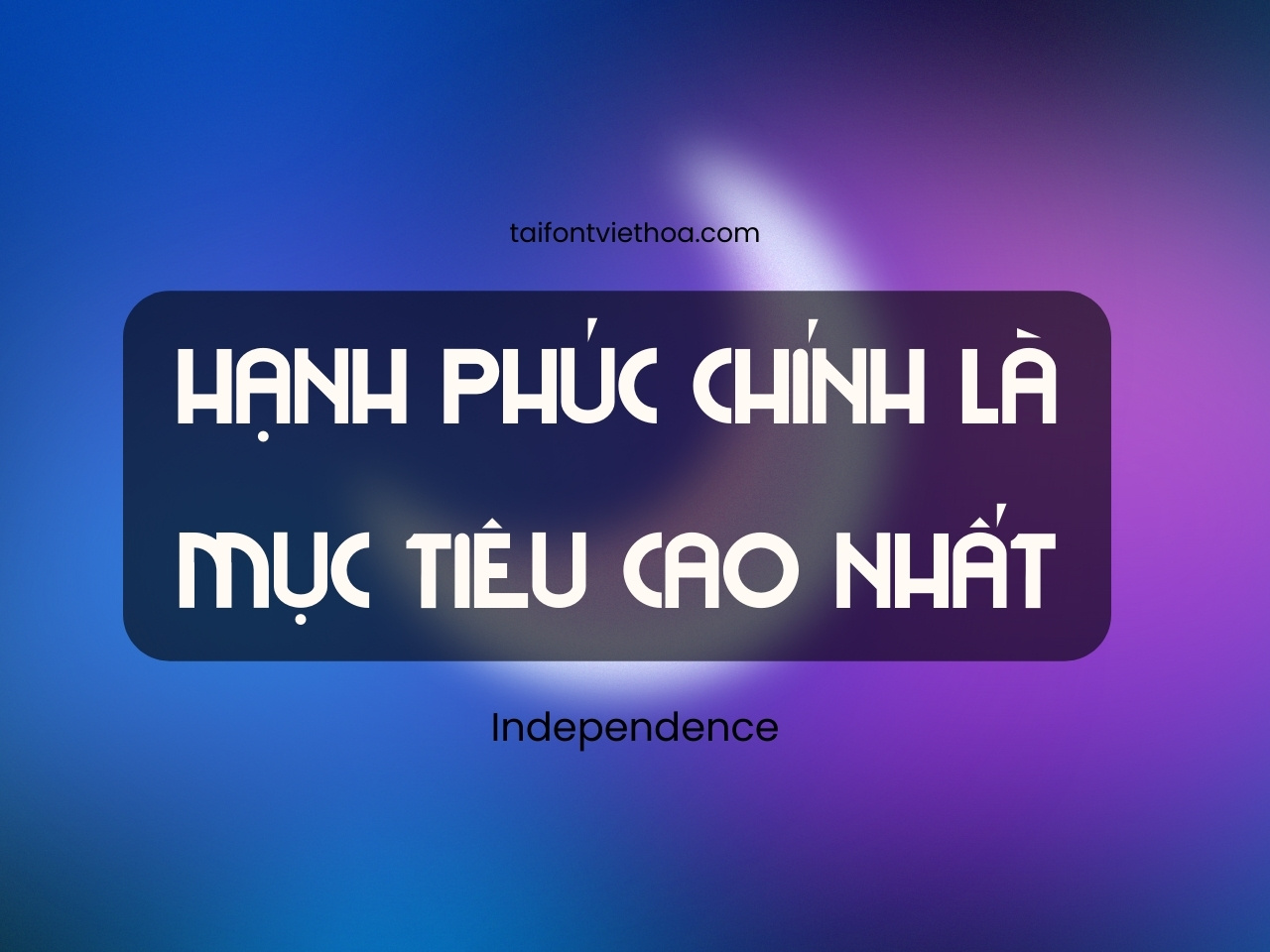
Tác giả Font: Đặng Anh Khoa
Giới thiệu về font Doc Lap và phiên bản Việt hóa
Doc Lap (Độc Lập) là một font chữ được sáng tạo bởi Đặng Anh Khoa – một nhà thiết kế font người Việt với định hướng tái hiện tinh thần dân tộc, văn hóa cổ truyền và lòng tự hào dân tộc qua từng nét chữ. Font mang cảm hứng từ các bảng hiệu xưa, khẩu hiệu, tranh cổ động giai đoạn đầu thế kỷ 20, với mục tiêu tạo nên một phông chữ mang đậm dấu ấn lịch sử nhưng vẫn có tính ứng dụng cao trong thiết kế hiện đại.
Phiên bản font Doc Lap được Việt hóa hoàn chỉnh bởi chính tác giả Đặng Anh Khoa, hỗ trợ đầy đủ bộ ký tự tiếng Việt chuẩn Unicode. Ngoài tiếng Việt, font còn hỗ trợ trên 70 ngôn ngữ sử dụng hệ chữ Latin, đáp ứng đa dạng nhu cầu thiết kế cả trong và ngoài nước. Font này đã được taifontviethoa.com sưu tầm, kiểm duyệt kỹ lưỡng và giới thiệu lại nhằm lan tỏa giá trị truyền thống thông qua hình thái chữ viết độc đáo, mạnh mẽ và gần gũi.
Đặc điểm thiết kế và khả năng ứng dụng đa dạng
Doc Lap thuộc nhóm font display mang cấu trúc mạnh mẽ, dứt khoát, với các nét chữ dày đều và góc cạnh rõ ràng. Font sử dụng hình khối chữ nhật là chủ đạo, tạo cảm giác vững chãi, khẳng định. Không có chân (sans-serif) nhưng lại mang hơi thở retro qua cách xử lý đầu chữ vuông vức và một chút phá cách trong độ cao các ký tự. Đây là lựa chọn hoàn hảo khi cần truyền tải thông điệp về sự kiên định, tinh thần cổ truyền hoặc cá tính riêng biệt trong thiết kế.
Font cực kỳ phù hợp trong các thiết kế như poster ngày lễ, khẩu hiệu tuyên truyền, ấn phẩm truyền thông giáo dục, sự kiện lịch sử, bao bì sản phẩm truyền thống, trò chơi mang màu sắc dân gian, hoặc các chiến dịch quảng bá thương hiệu Việt. Đặc biệt, Doc Lap còn có thể được sử dụng cho các dự án thiết kế dịp lễ Quốc khánh, Tết cổ truyền, Trung thu hoặc lễ hội văn hóa dân gian.